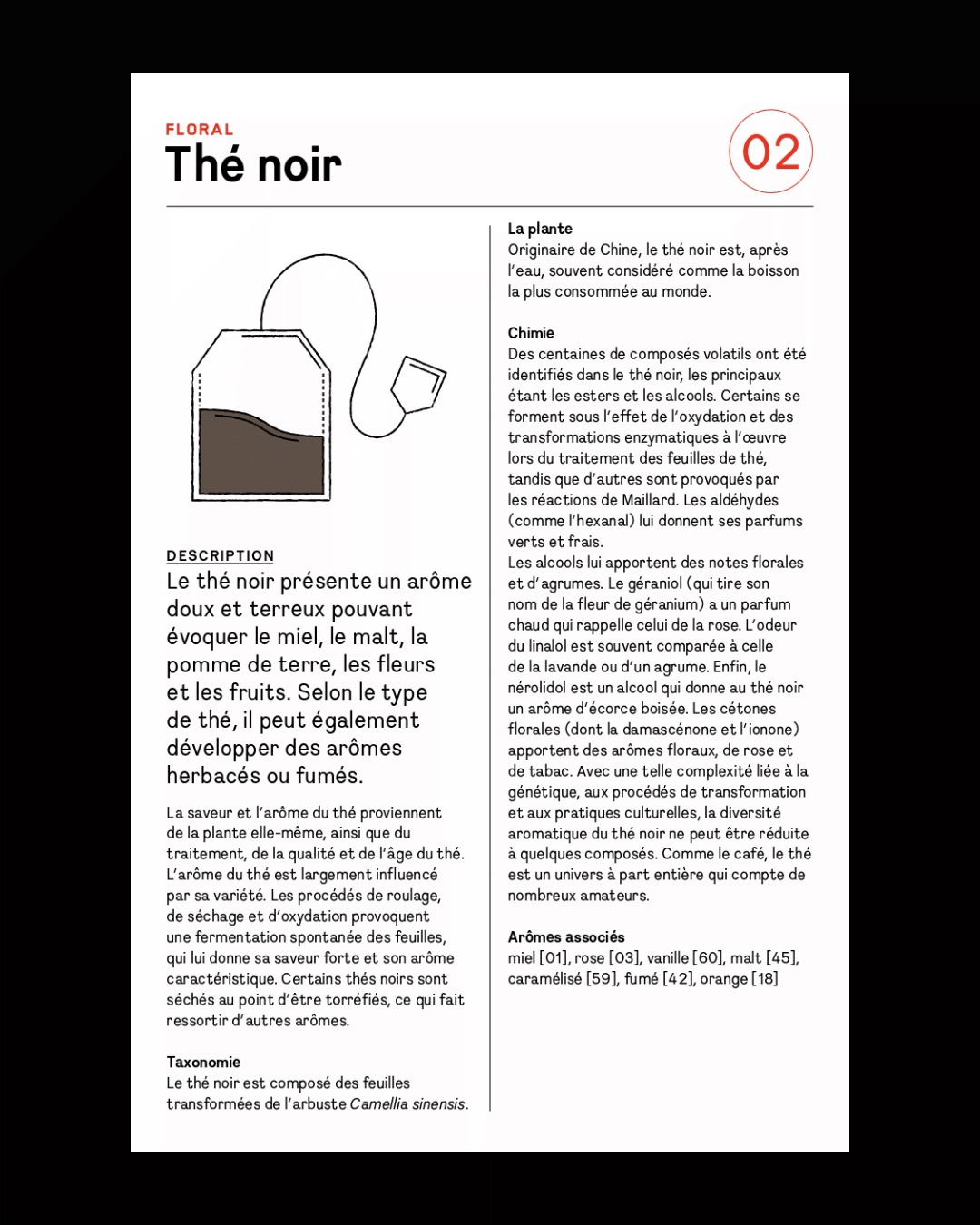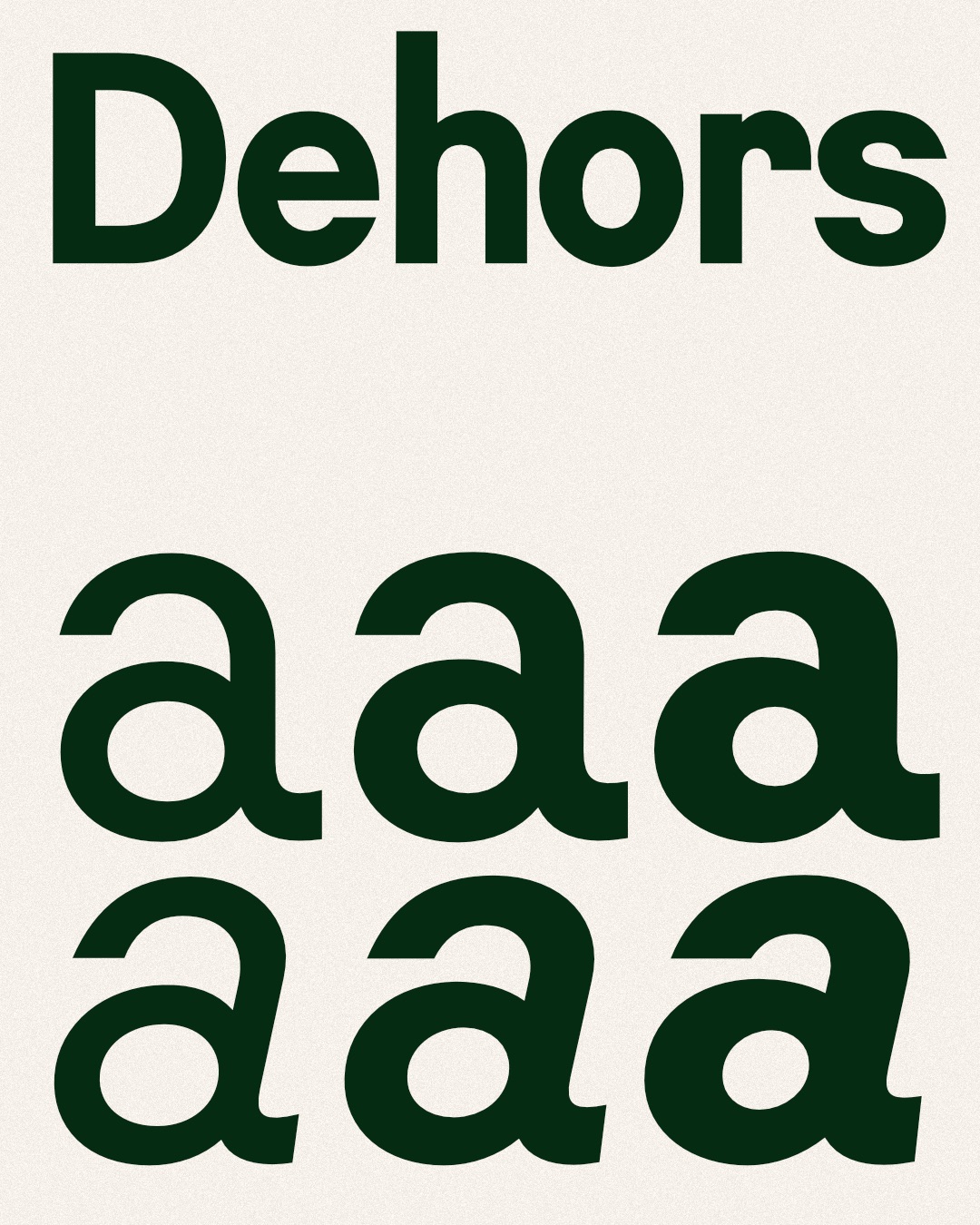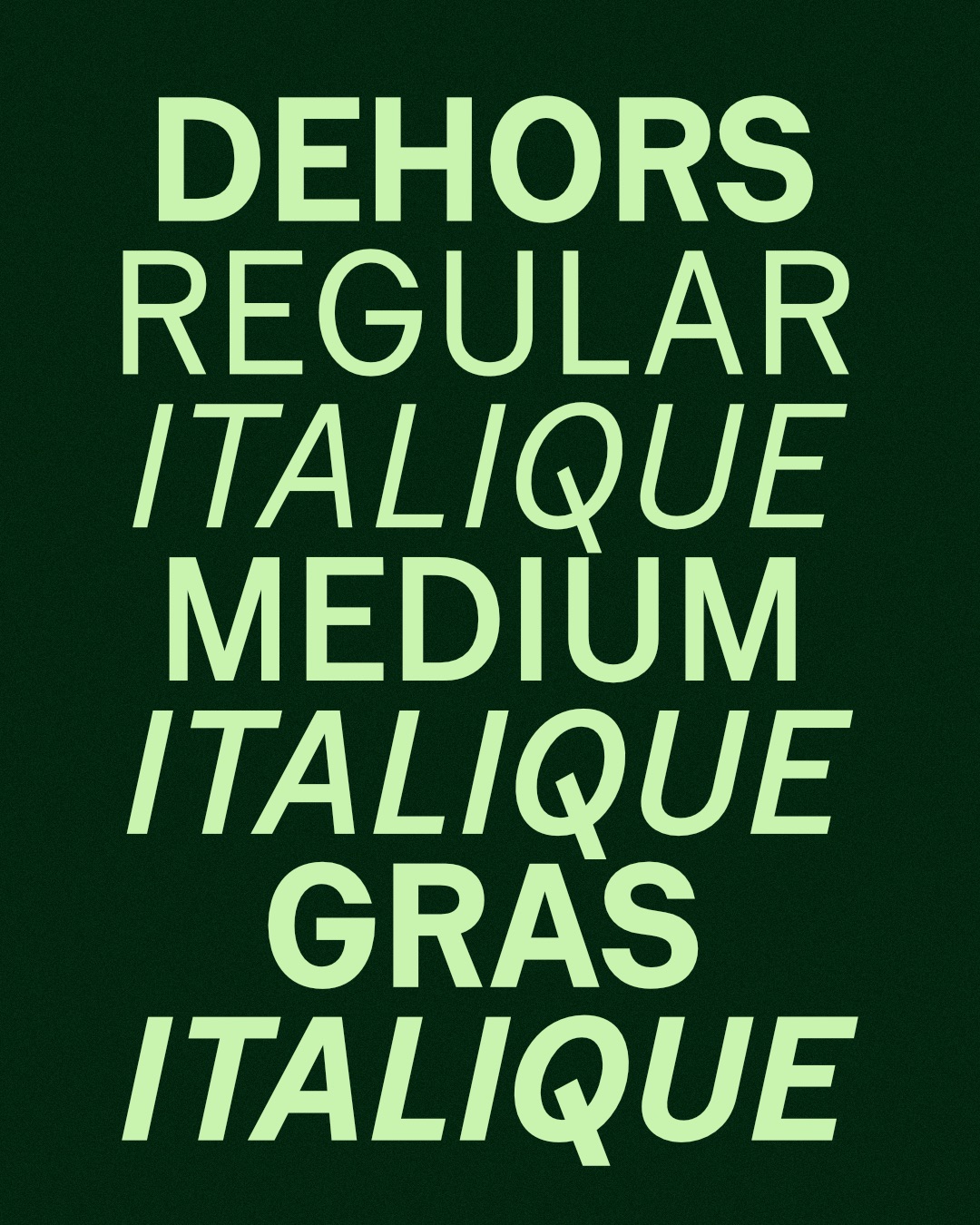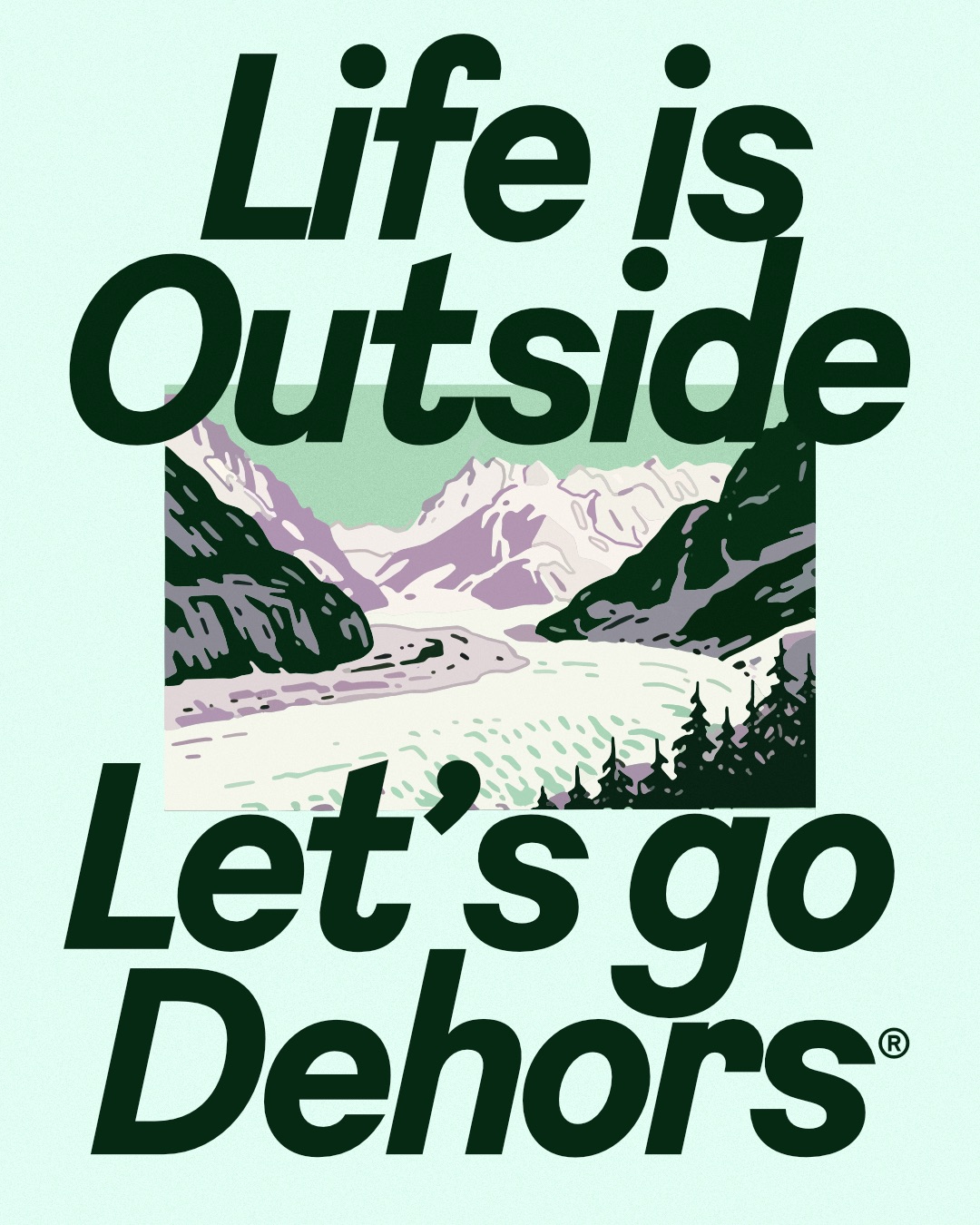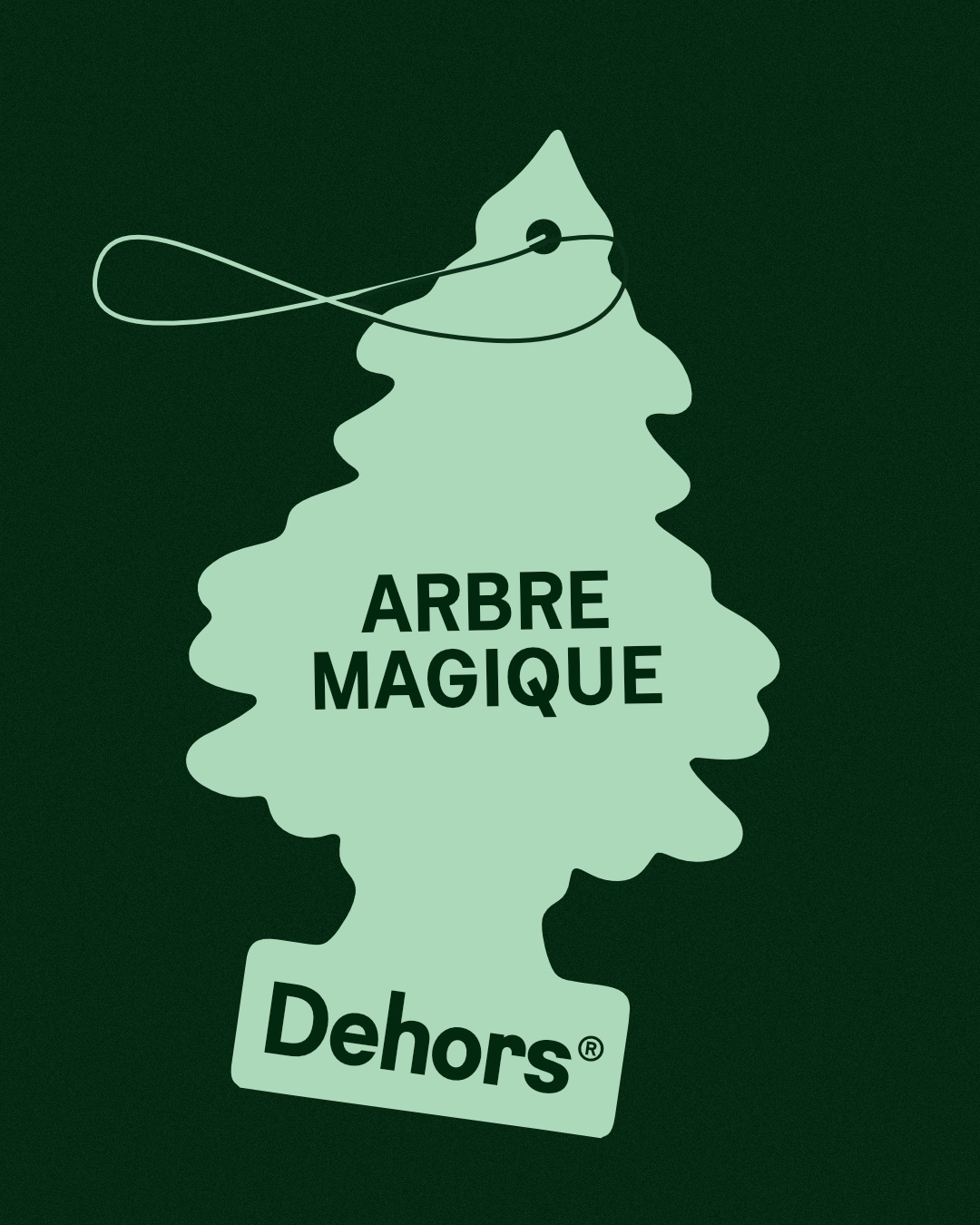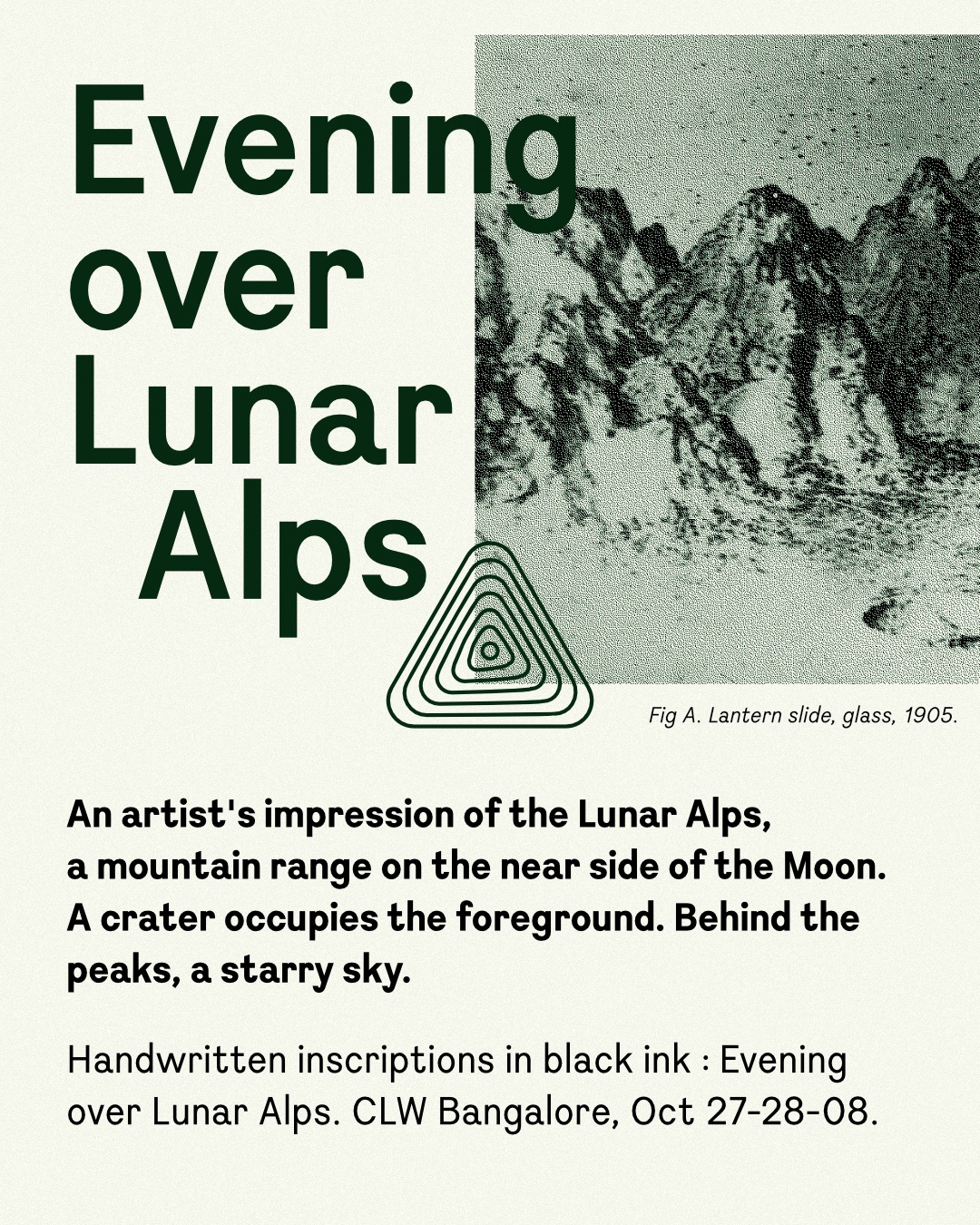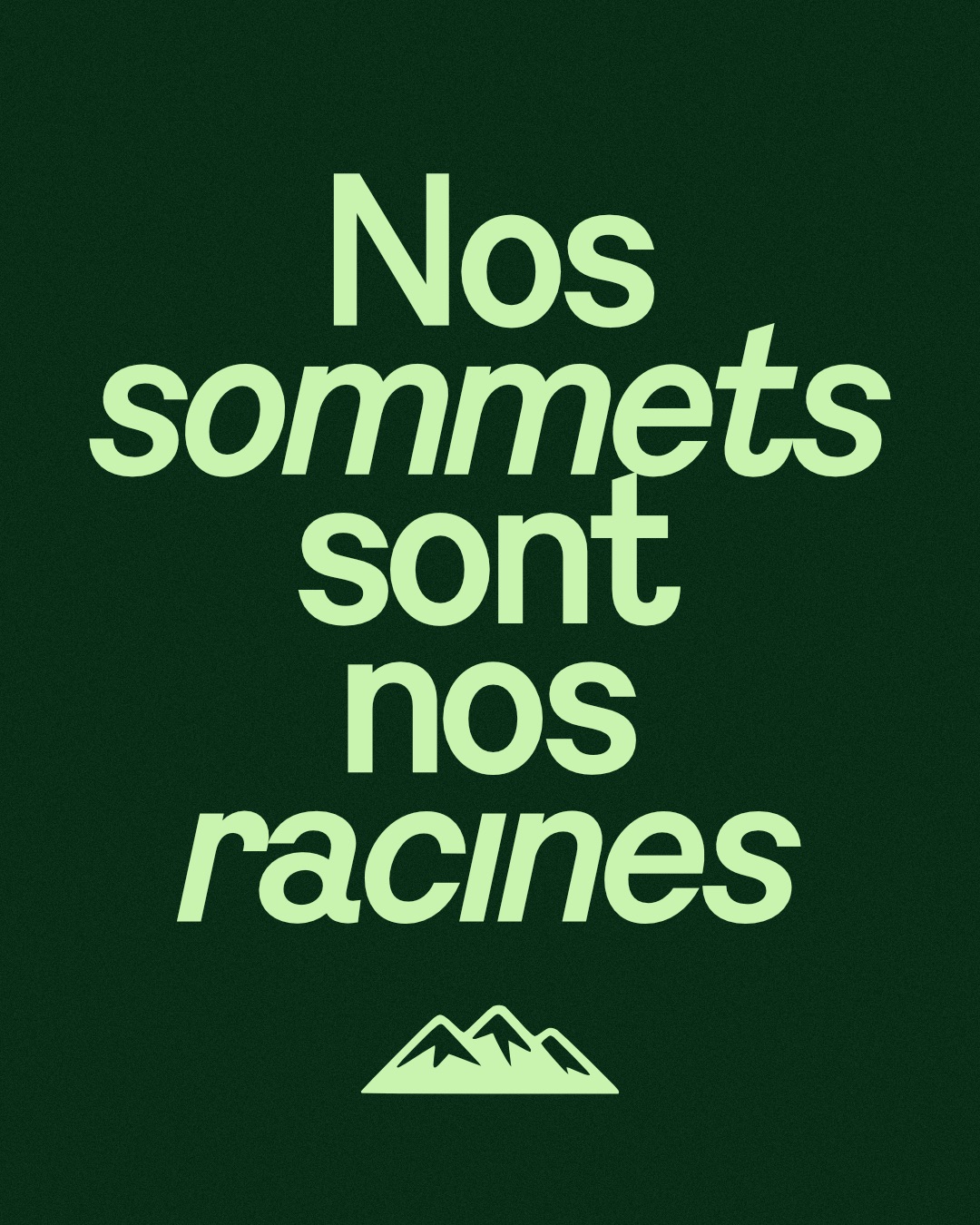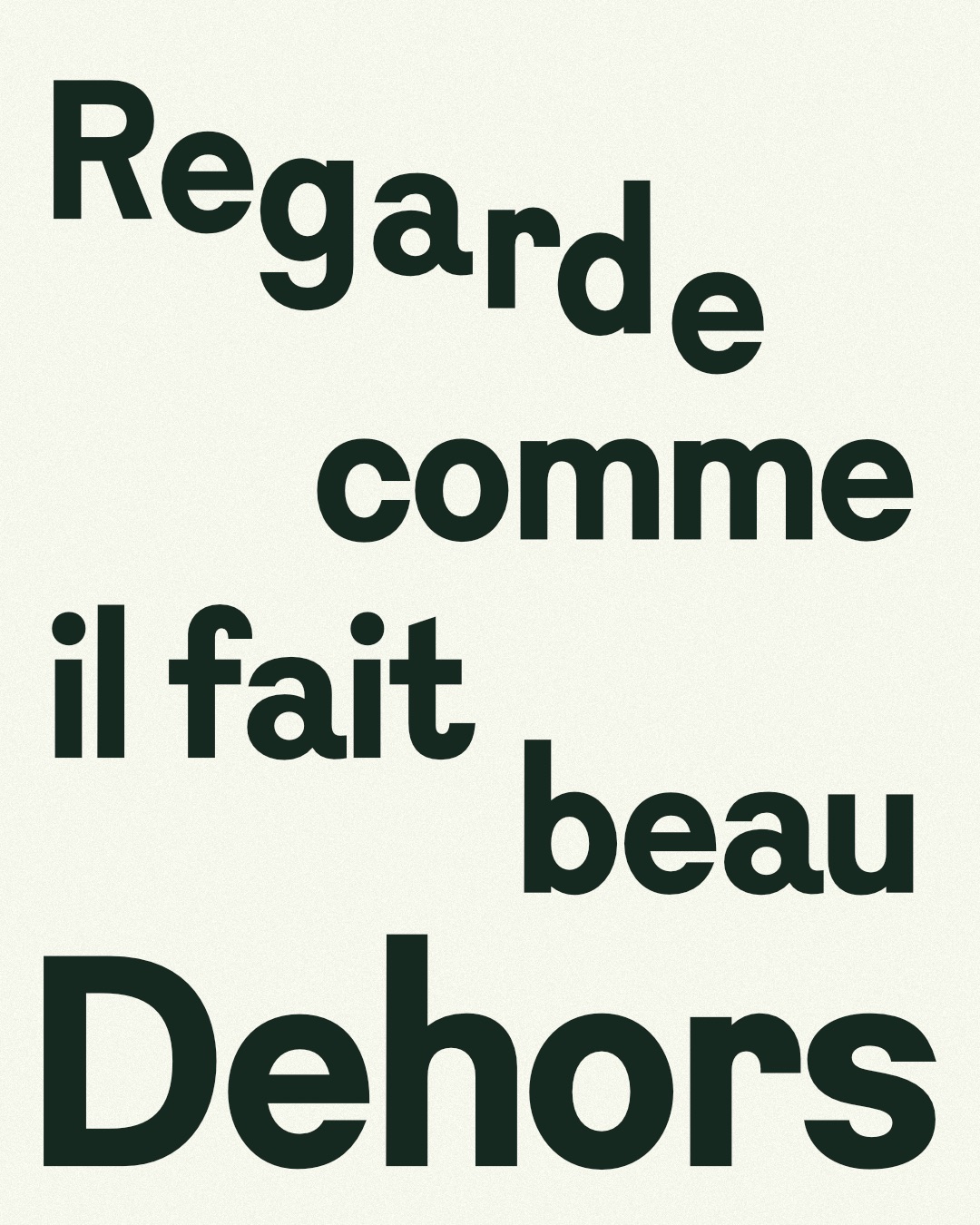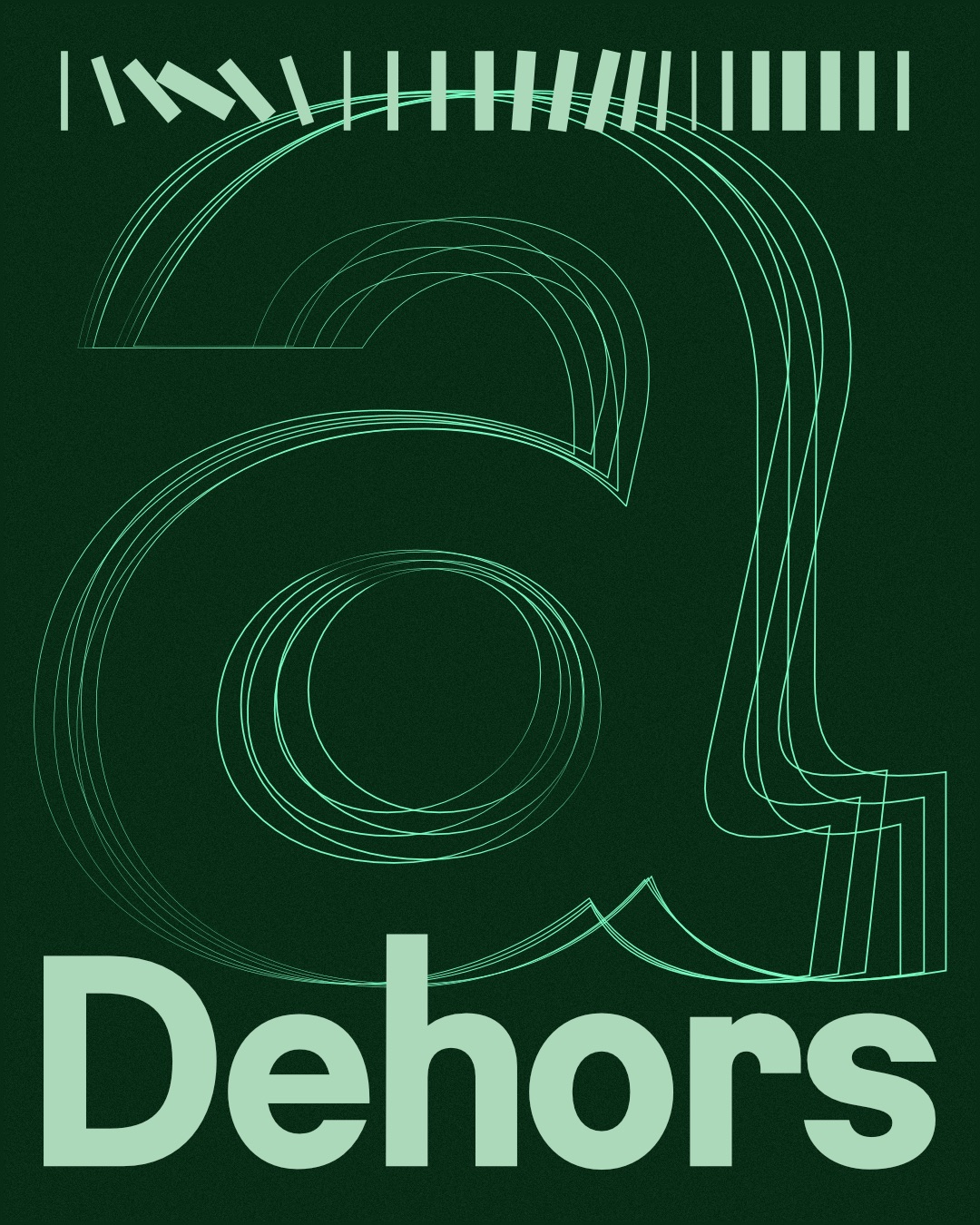
6 styles & variable fonts
Dehors est une famille sans sérif en six styles et fonte variable, dessinée par Anton Moglia. Dérivée de la Dauphine (Charles Mazé & Coline Sunier), elle reprend son héritage cartographique tout en proposant des proportions restructurées, un spacing et un kerning entièrement revus, et une palette de graisses étendue et variable : 6 styles, du Regular au bold et leurs italiques. Merci à Charles Mazé & Coline Sunier pour leur travail original sur la Dauphine, fondation de ce projet. Dehors a été dessinée à l'initiative de Clément Charbonnier-Bouet et Jean-Charles Bassenne, pour la communication de l'artiste Carolina E. Santo.
« Dehors » désigne un lieu ou une position situé au-delà des limites d'un espace clos.
| Nom | Dehors |
| Styles | Regular, Italic, Medium, Medium Italic, Bold, Bold Italic |
| Langues supportées | Support linguistique Latin Occidental (Western European). Couvre les principales langues d’Europe de l'Ouest et des Amériques. |
| Information | Dehors est une famille sans sérif en six styles et fonte variable, dessinée par Anton Moglia. Dérivée de la Dauphine (Charles Mazé & Coline Sunier), elle reprend son héritage cartographique tout en proposant des proportions restructurées, un spacing et un kerning entièrement revus, et une palette de graisses étendue et variable : 6 styles, du Regular au bold et leurs italiques. Merci à Charles Mazé & Coline Sunier pour leur travail original sur la Dauphine, fondation de ce projet. Dehors a été dessinée à l'initiative de Clément Charbonnier-Bouet et Jean-Charles Bassenne, pour la communication de l'artiste Carolina E. Santo. |
| Designer | Anton Moglia |